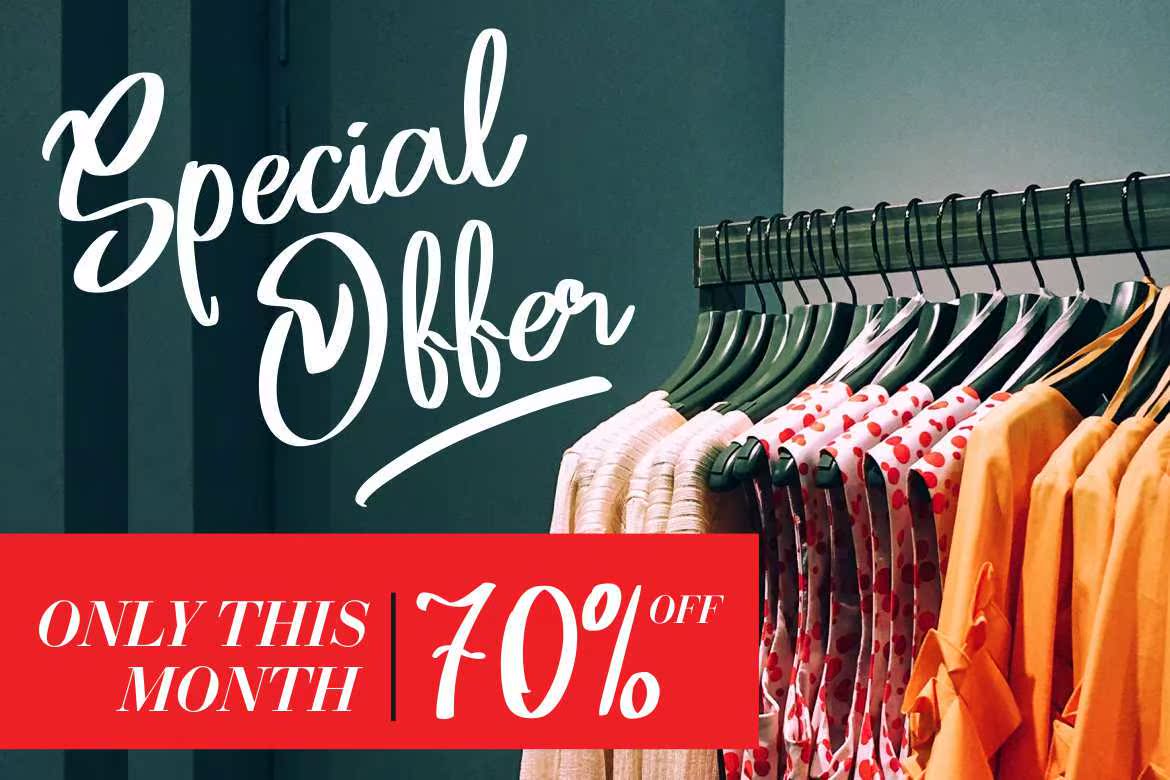
英格兰是一个带有手写字体的现代手写字体。此字体外观为所有设计和推荐的字体、海报、品牌、报价或任何需要的字体和字体。此字体具有混合和风格设置交替字符,您可以在您的设计软件中访问OpenTypePanel中的所有选项。England是一个带有手写字体样式的现代手写字体。此字体外观为任何设计,并对草稿、海报、品牌、报价或任何需要的内容进行了详细说明。此字体具有混合和风格设置替代字符,您可以从设计软件中的OpenTypePanel访问AllAlternates。